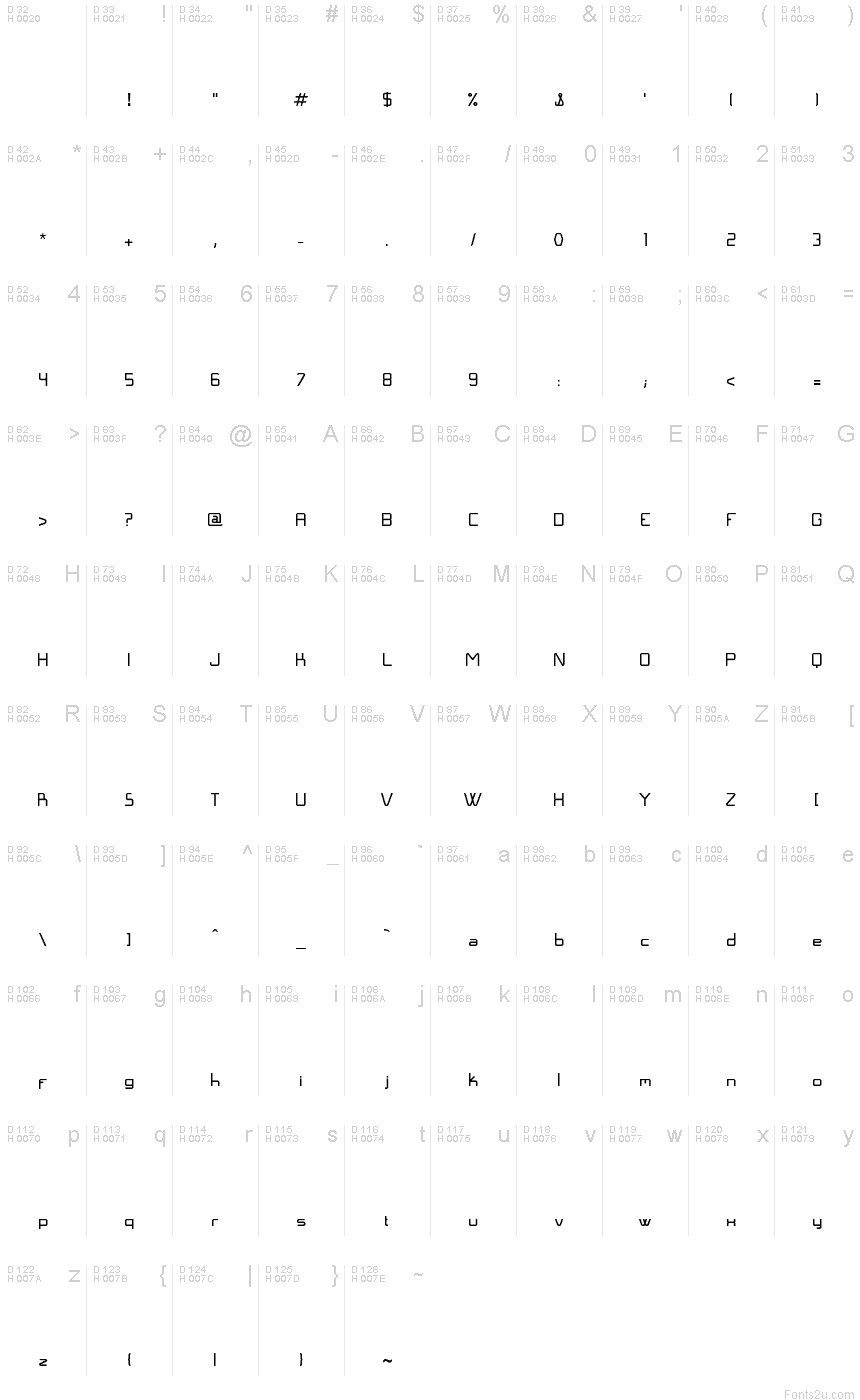
Langó Normal
Il font Langó di Josep Patau i Bellart e Astramat Antaviana Typeface Division è un carattere display techno caratterizzato da forme squadrate, angoli smussati e una costruzione aperta e rotonda. I suoi rettangoli arrotondati, le curve strette e le aste verticali angolate creano un ritmo essenziale e ingegneristico, preciso senza risultare severo.
Langó è perfetto per il branding tecnologico, titoli di poster, logotipi, menu di gioco, interfacce di app e l'identità visiva di startup, grazie alle sue forme che rimangono nitide e ben strutturate anche in formati ridotti. È ideale anche per accenti editoriali e brevi marchi testuali, dove un look codificato e su misura è più importante della leggibilità in testi lunghi.